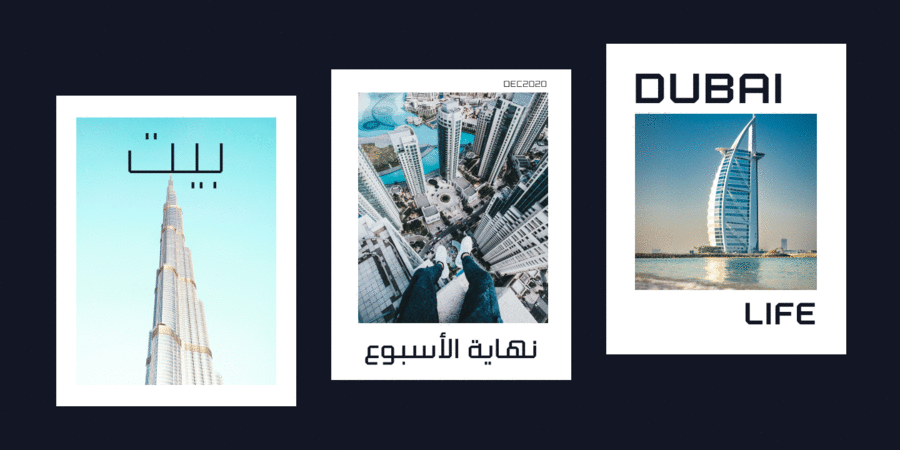
Геометричний ґротеск, пом'якшений зовні і гострий всередині. Оновлене і доповнене підтримкою арабської мови сімейство включає розширений набір символів, підтримує більшість латинських мов, і навіть в'єтнамську! Klapt, який може бути і жирним і дуже тонким, призначений для різного дизайну, від брендингу й фірмового стилю до багатосторінкових видань для друку та екранів. Він відмінно підходить для акціденціі, особливо для заголовків, постерів, журналів, обкладинок, логотипів. Не соромтеся ділитися своїми дизайнами з використанням Klapt чи просто зв'яжіться з автором hi@seventype.com. Шрифт розробила Віторія Невес у 2020 році.
Асоціації з сімейством шрифтів Klapt ArabicОсобистість і характер гарнітури:
рівний, квадратний, точний, логічний, холодний, автоматичний, техногенний, твердий, статичний, різкий, чіткий, стійкий, стабільний, тонкий, легкий, прямокутний, міський, сучасний, машинний, гострий, інженерний, урбаністичний, креслярський, скляний, крихкий, футуристичний, дротяний, Простий, надійний, впевнений, сталевий, космічний, байдужий, гранчастий, рубаний, переконливий, серйозний, сильний, індустріальний, залізний, мужній, військовий, армійський, промисловий, залізничний, ігровий, спортивний, робочий, кінематографічний
конструктор, креслення, архітектура, інженер, автоматика, урбаністика, наука, дизайн, Місто, статистика, гаджет, електроніка, технології, фантастика, космос, інструмент, робот, гра, прилад, айтішник, IT, айті, андроїд, залізо, коворкінг, рентген, астрономія, авто, промисловість, війна, армія, зброя, завод, металургія, верстат, тара, склад, порт, ящик, патрони, техніка, ремонт, депо, шолом, уніформа, вагон, авіація, літак, автомат, шутер, екшен, транспорт, страйкбол, взуття, залізниця, кубики, лего, комп'ютерна гра, спорт, машинобудування, охорона, захист, паливо, поліція, будівництво, цегла, автобус, робочий, кіно, кіберспорт Гарнітура має ознаки стилів: